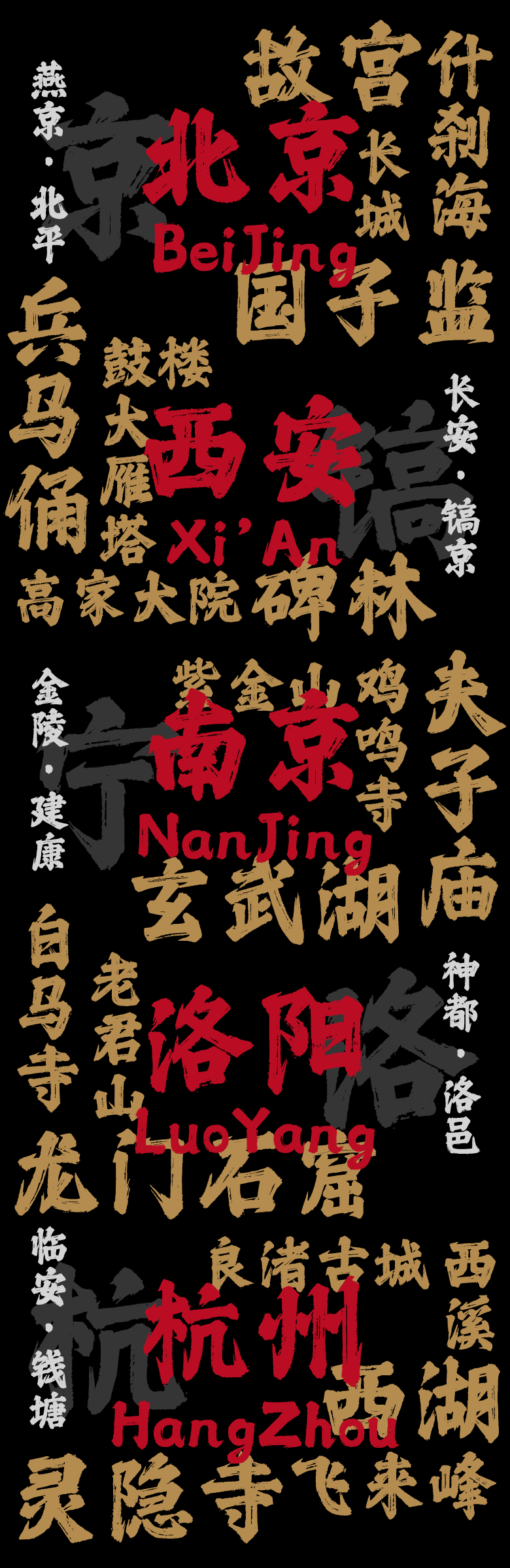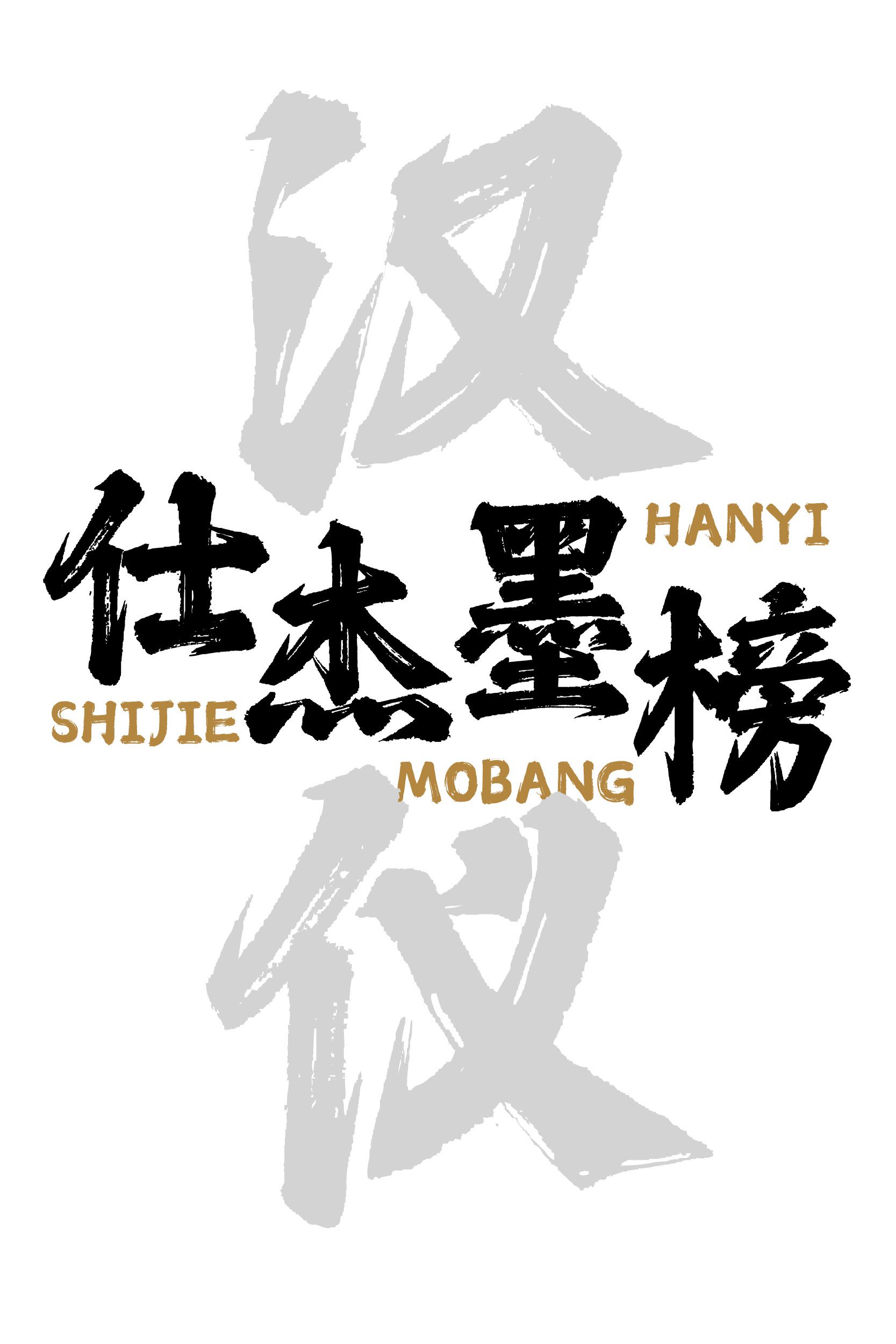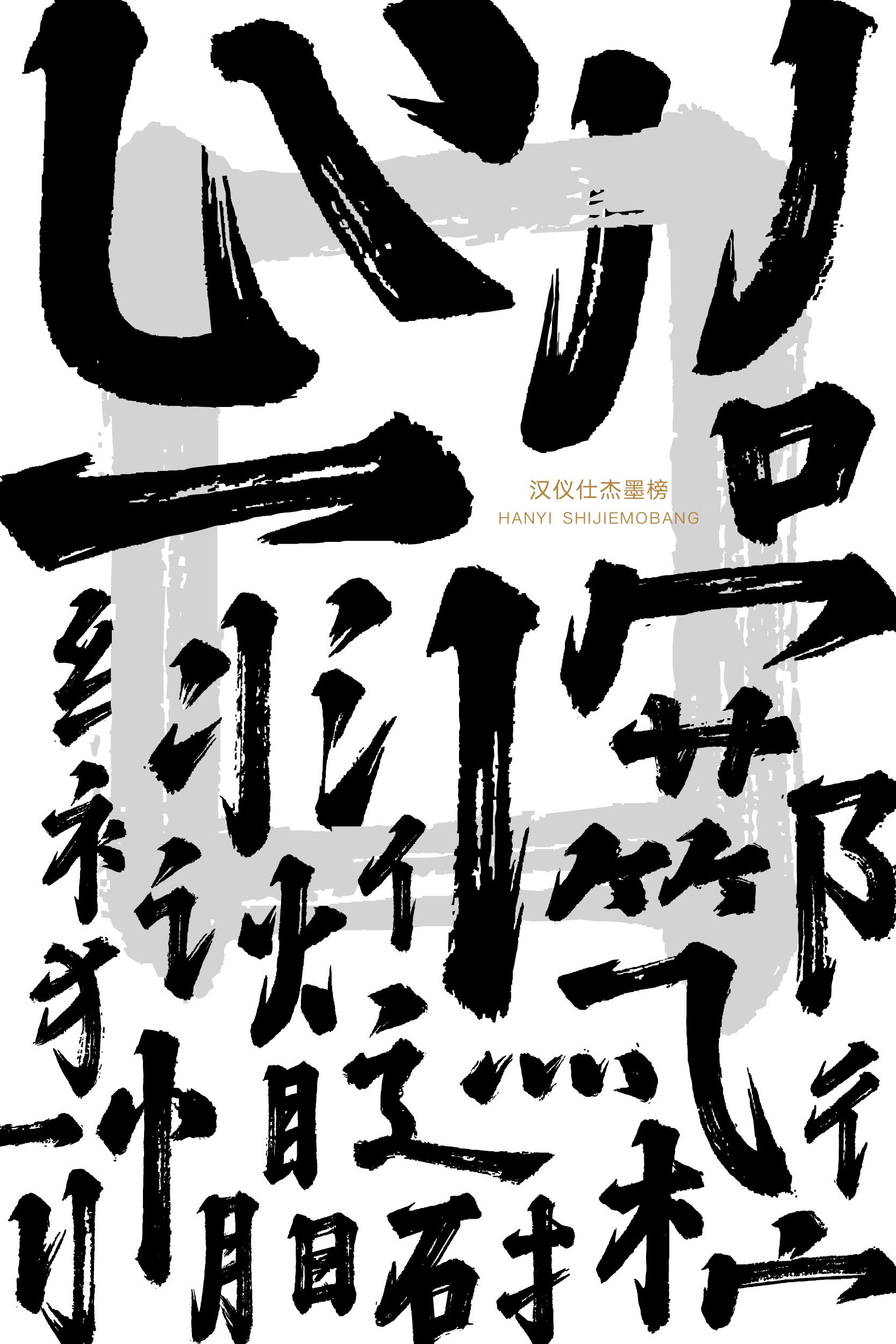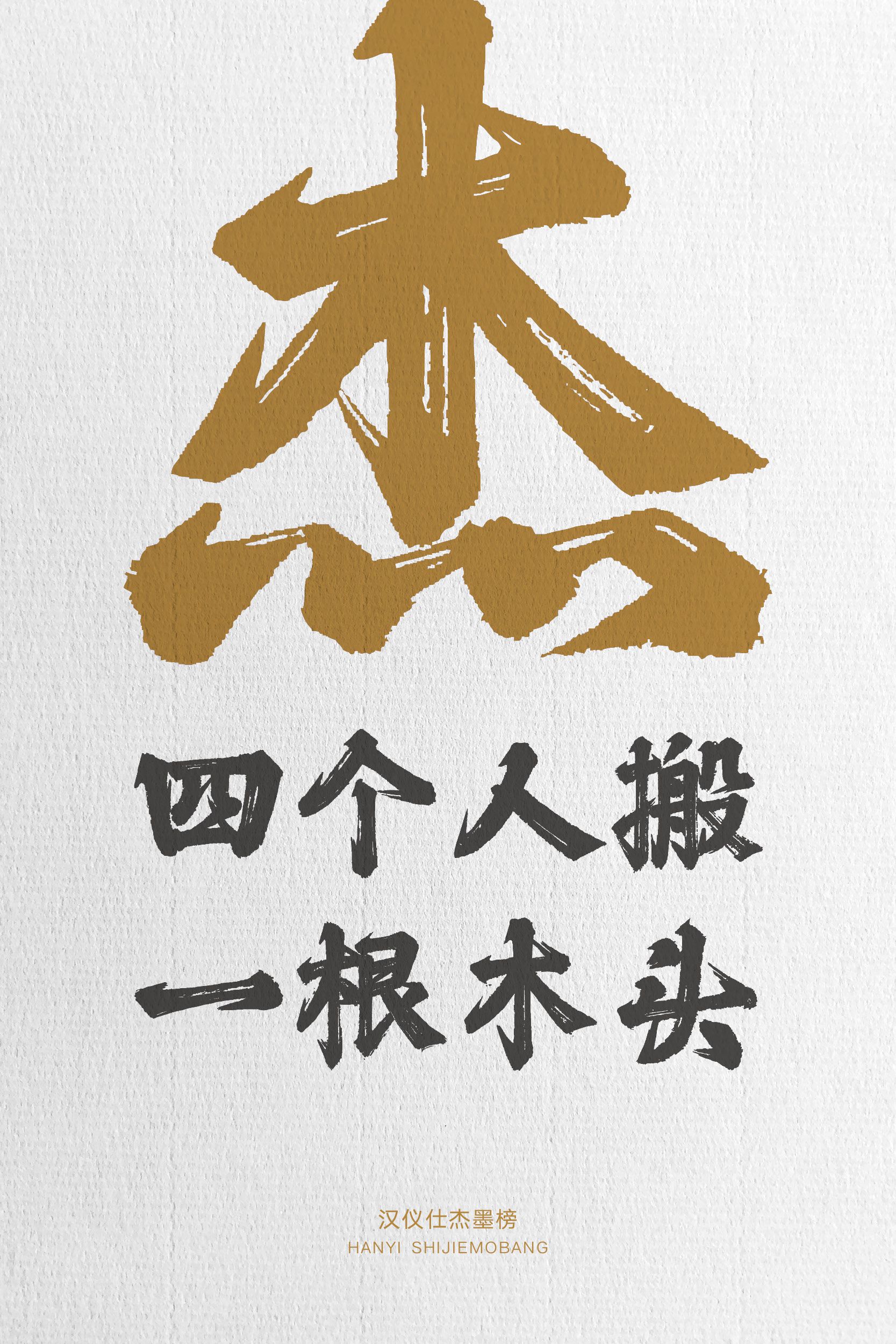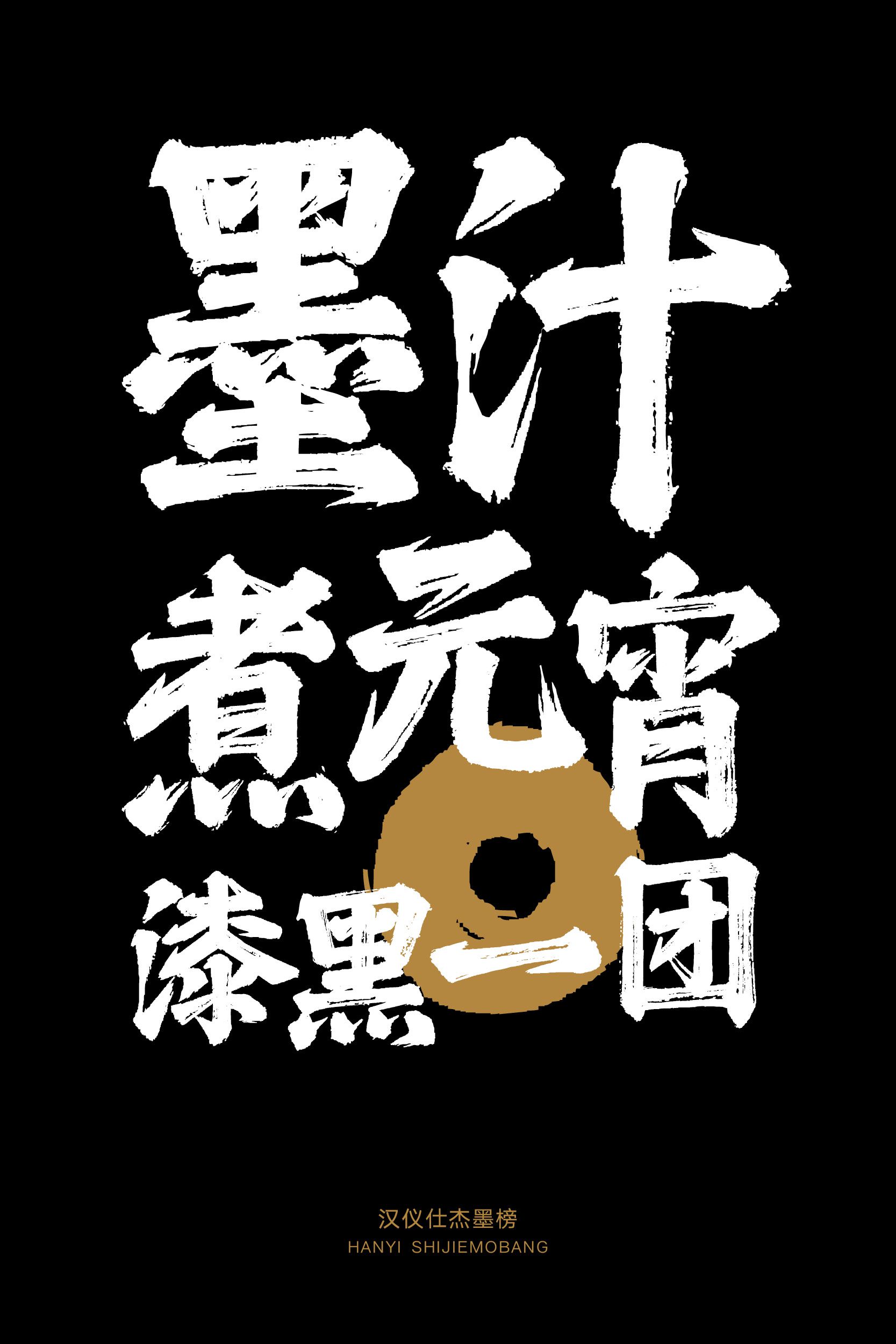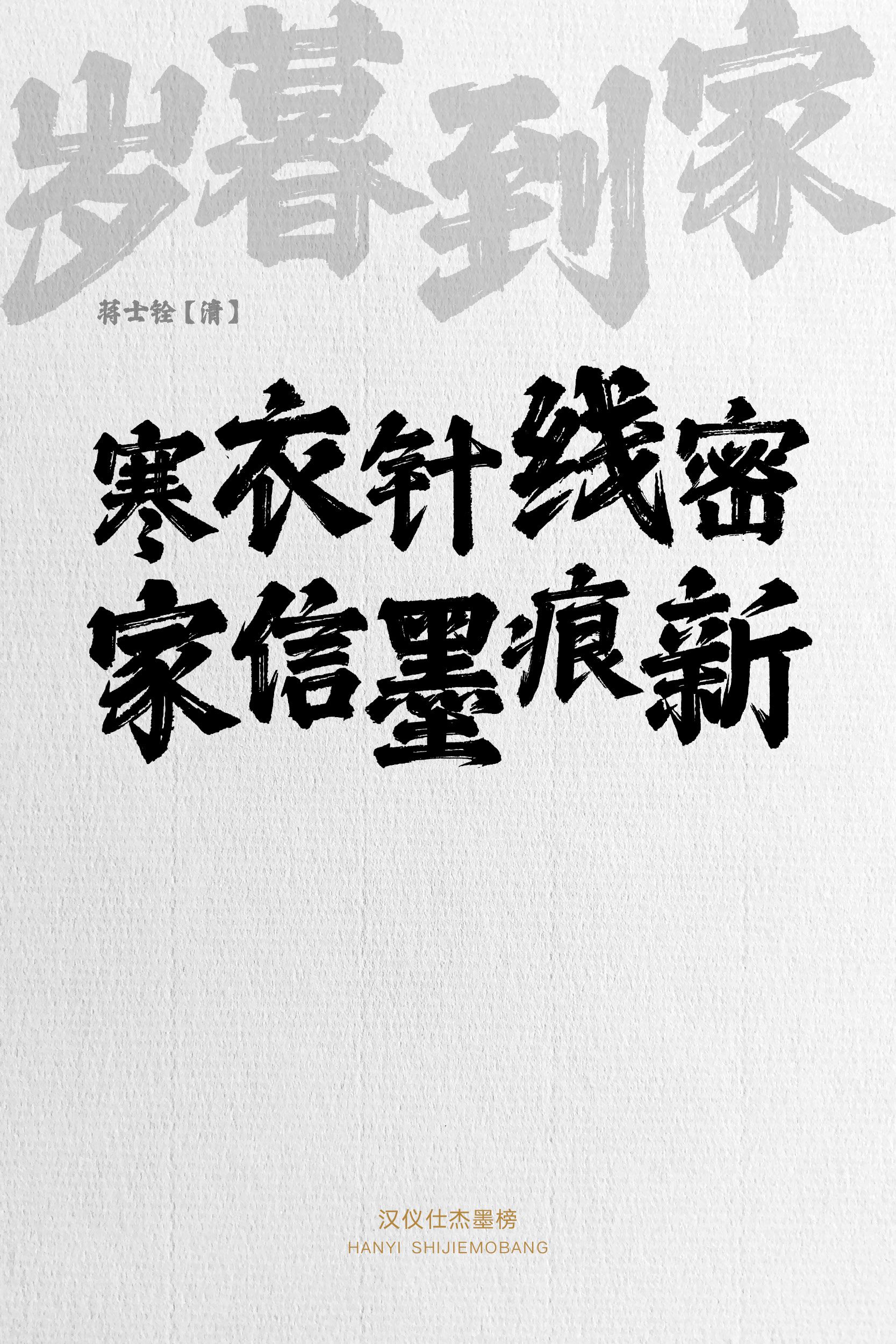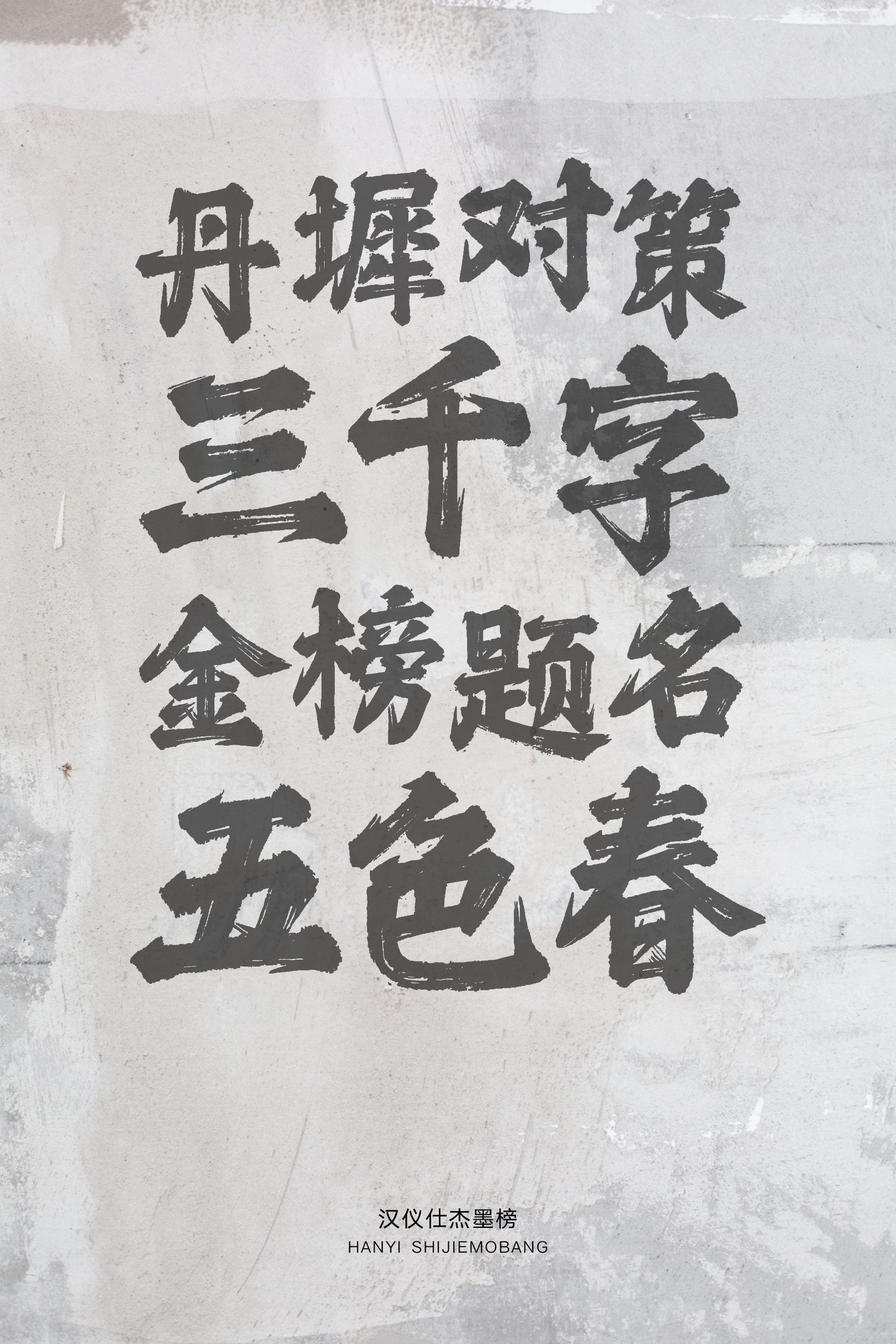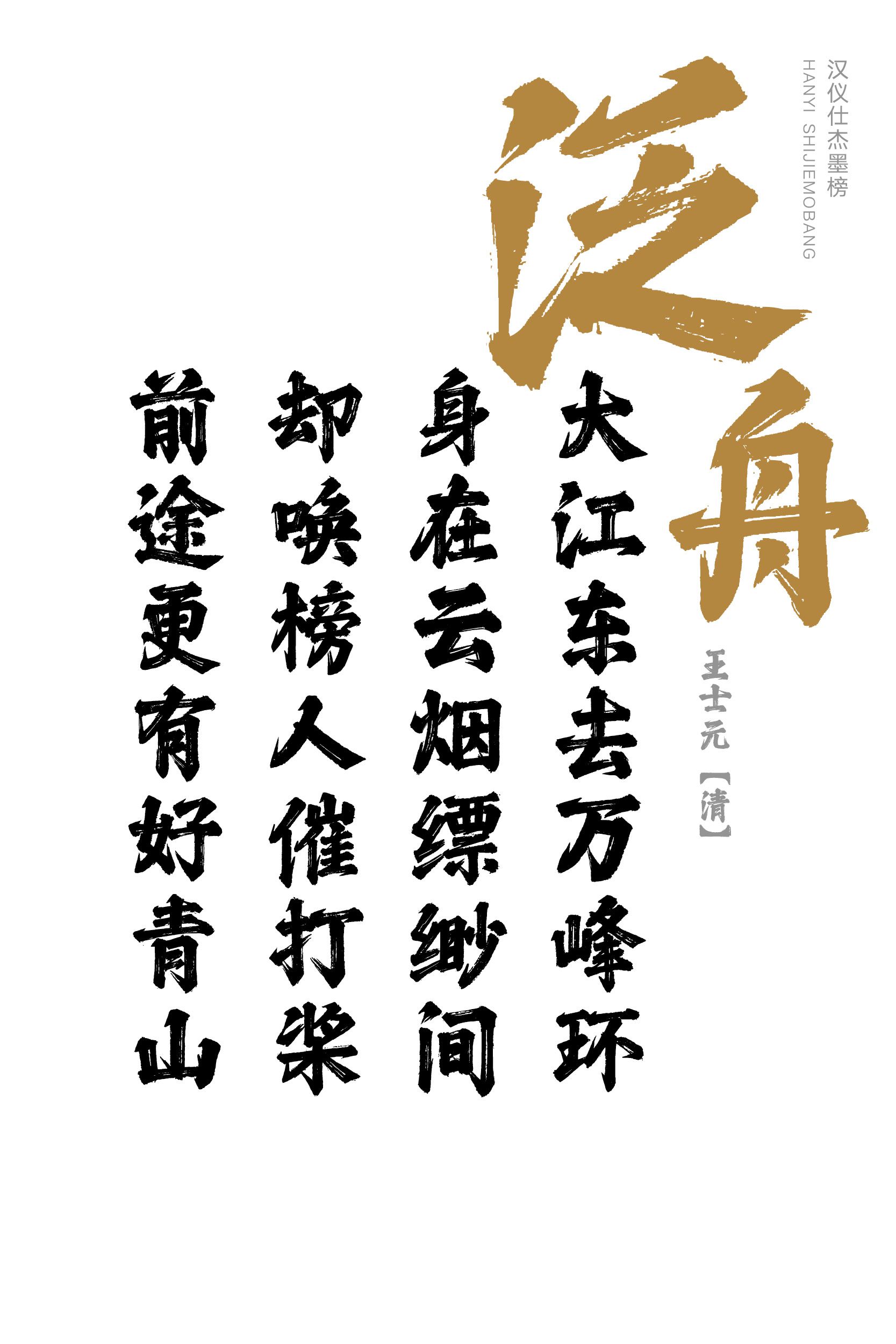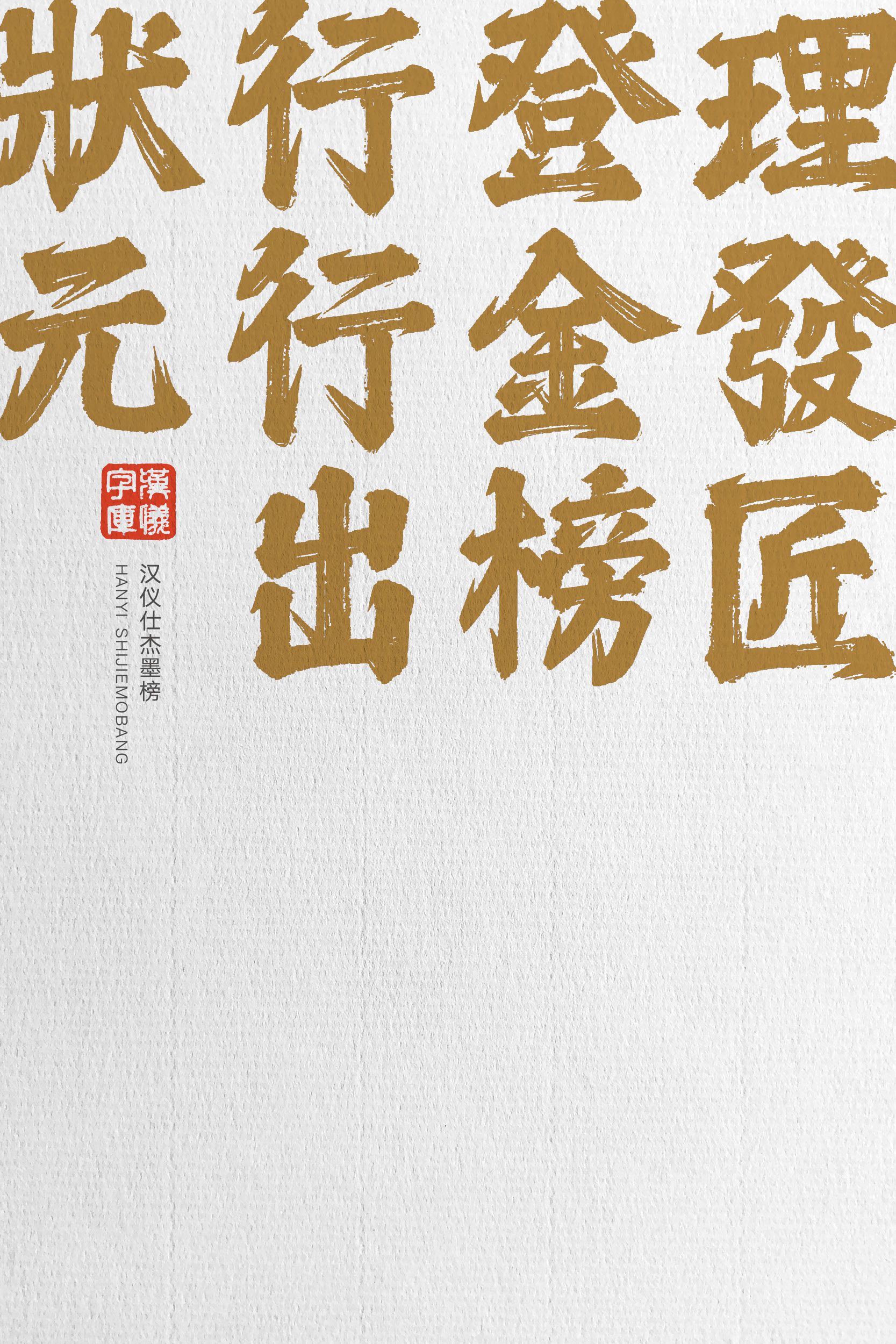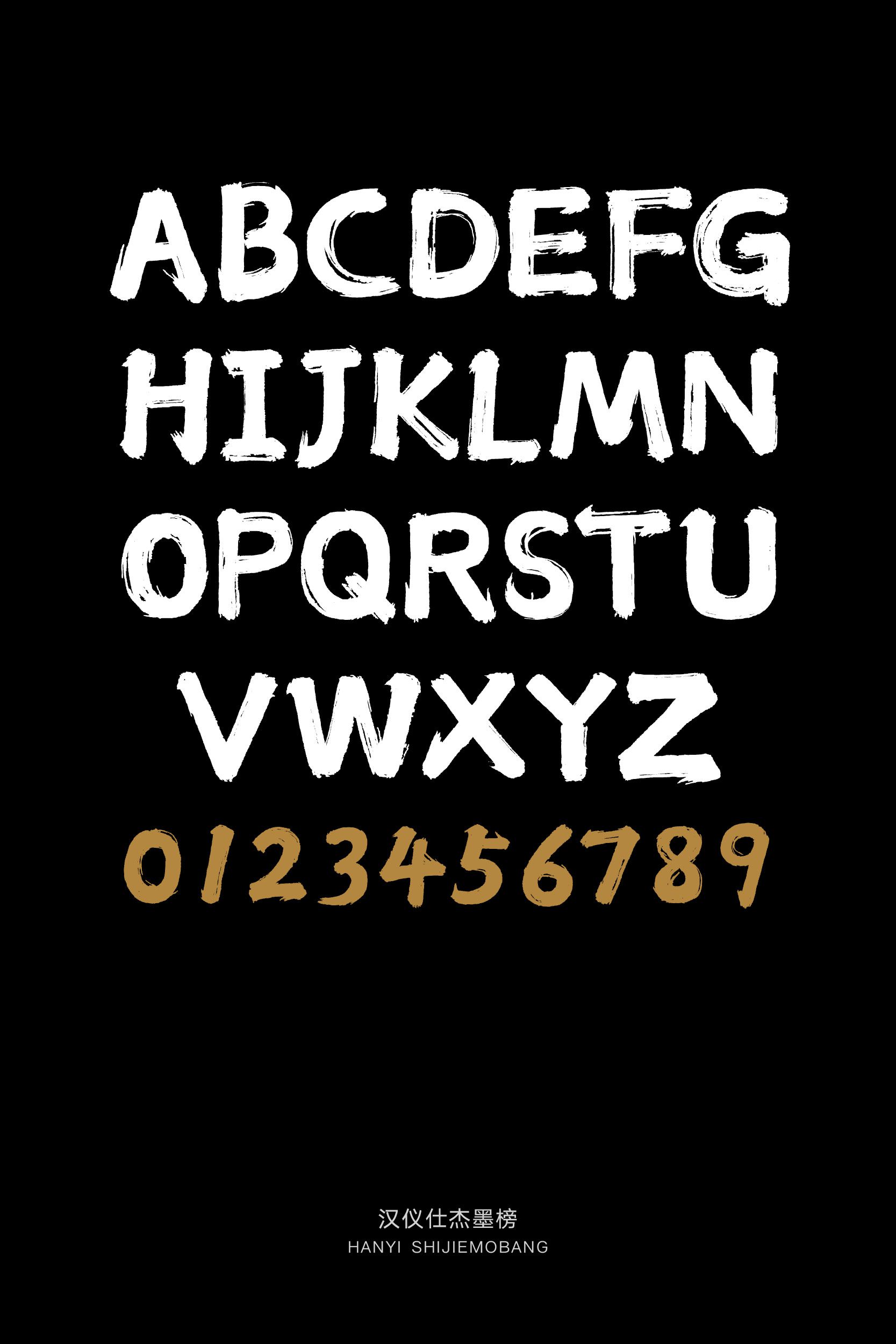
雄浑苍健、气势磅礴的榜书字体
书写字体
书写 / 稳重 / 雄健
标志 / 广告 / 书籍 / 杂志
游戏 / 动漫 / 影视 / 包装
汉仪仕杰墨榜是一款带有强烈个性风格的榜书字体,雄浑苍健、气势磅礴。相比于一般的榜书字体,这款字体有着更加雄健硬朗的笔画线条、更加潇洒利落的连笔,以及更加酣畅淋漓的飞白。整体字形在保证视觉冲击力的同时有着较高的字形识别度与版面稳定性,排版效果稳重而大气。这款字体适合作为标题字体用于文旅休闲、周边文创、影视娱乐等场景。
汉仪仕杰墨榜|字体特征
字形端正,重心平稳,字形大小相近,整体气势磅礴。
笔画起收相互照应,行笔均匀有力,有着榜书遒劲的笔力。
笔画线条雄健硬朗,连笔潇洒利落,飞白酣畅淋漓。
汉仪仕杰墨榜的西文部分字形同样端正稳重,间以连笔和飞白。
汉仪仕杰墨榜|排版应用
这款字体雄浑苍健、气势磅礴,排版效果端正规整,传达稳重大气之感。